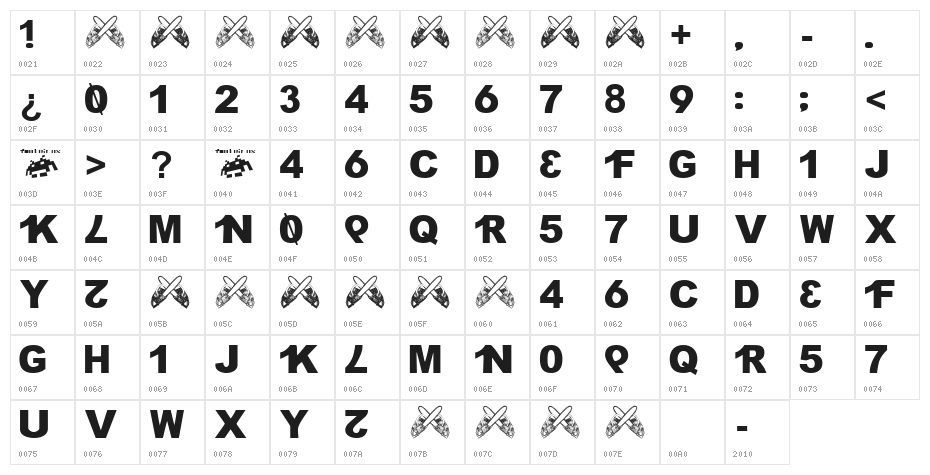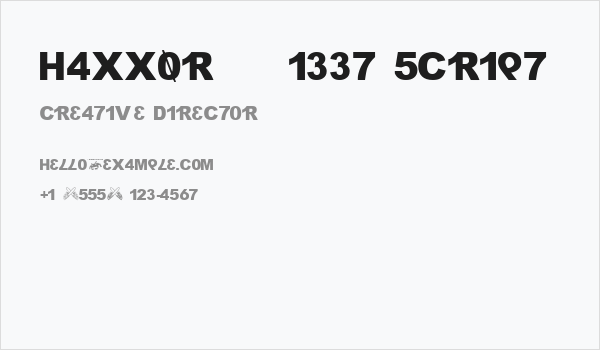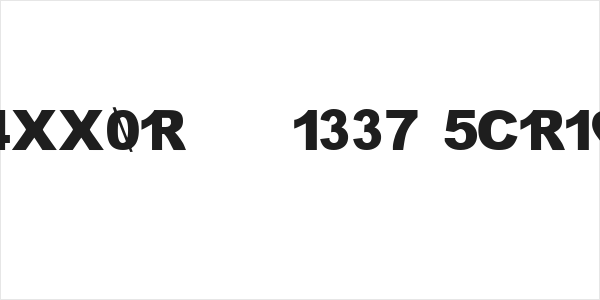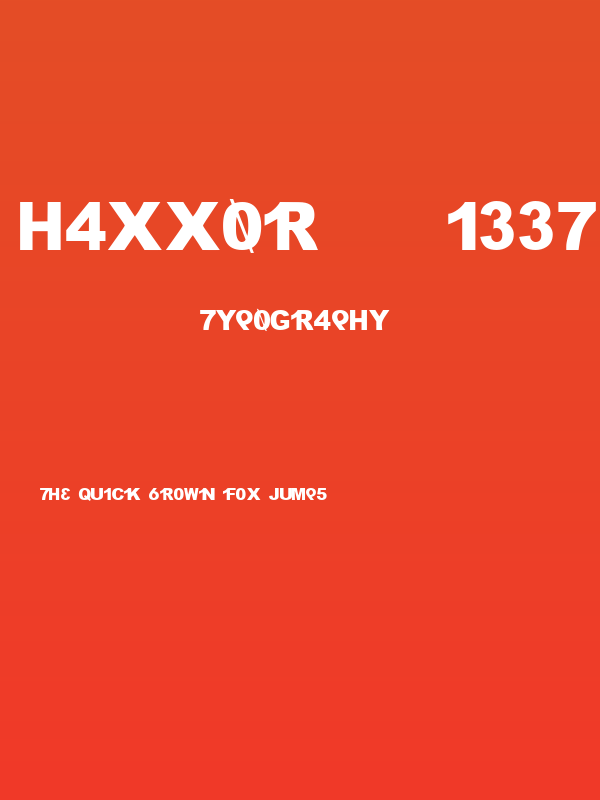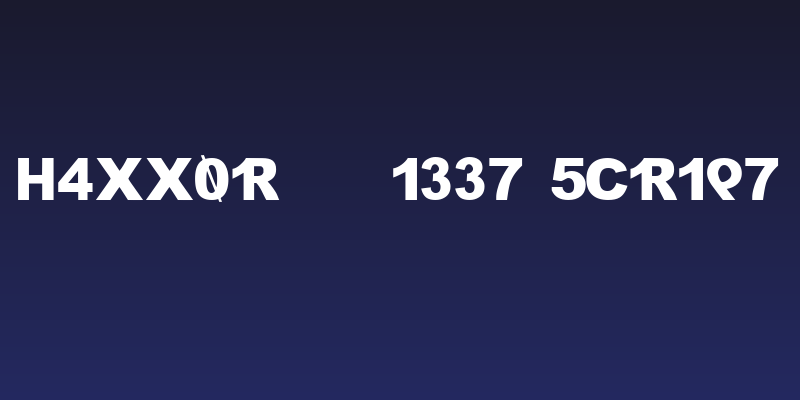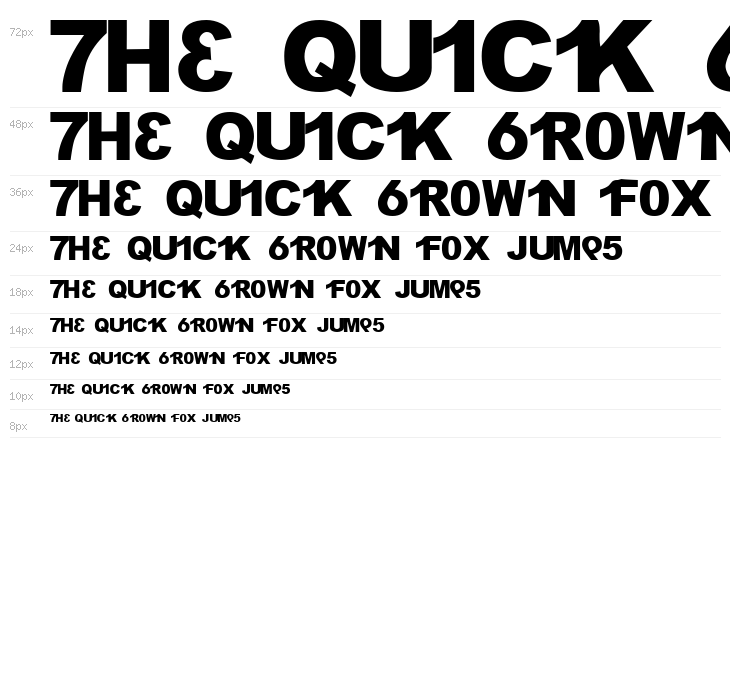
H4XX0R 1337 5CR1P7 Font
✎ Crazy
| Stile generale | Futuristic, Edgy |
| Progetti proposti | Ideal for tech-related branding, video game titles, posters, and any project needing a modern, edgy look. |